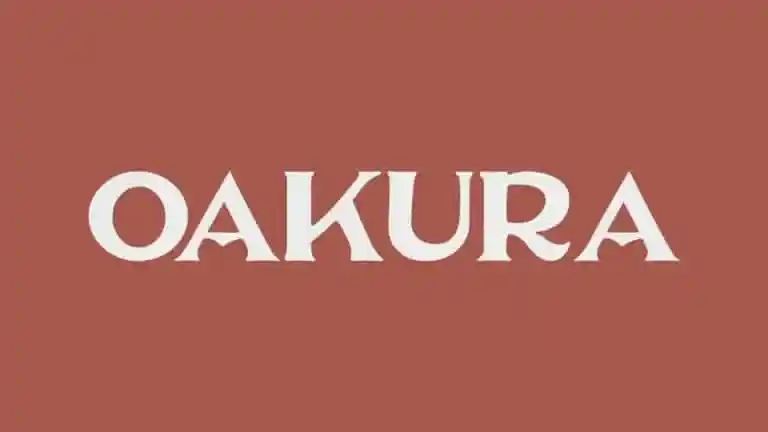
A Oakura Serif Font é uma versão moderna de tipografia que oferece um toque vintage elegante para projetos de design. Esta font foi criada por Andrew McMillan, inspirada nos selinhos dos sinais em um salão comunitário chamado Oakura, localizado em Taranaki, Nova Zelândia. Ela combina a delicadeza do estilo serif tradicional e o ar vintage da arte grafica que podemos encontrar nas placas de sinalização da área. Sacre Blue é uma opção perfeita para aqueles designers procurando um tipo especializado para destacar seus trabalhos nos campos de lifestyle refinado, editorial ou em criações infográficas. Seja para criar um projeto elegante ou artístico, a Oakura Serif Font certamente trará um toque de sofisticação e originalidade ao seu design.